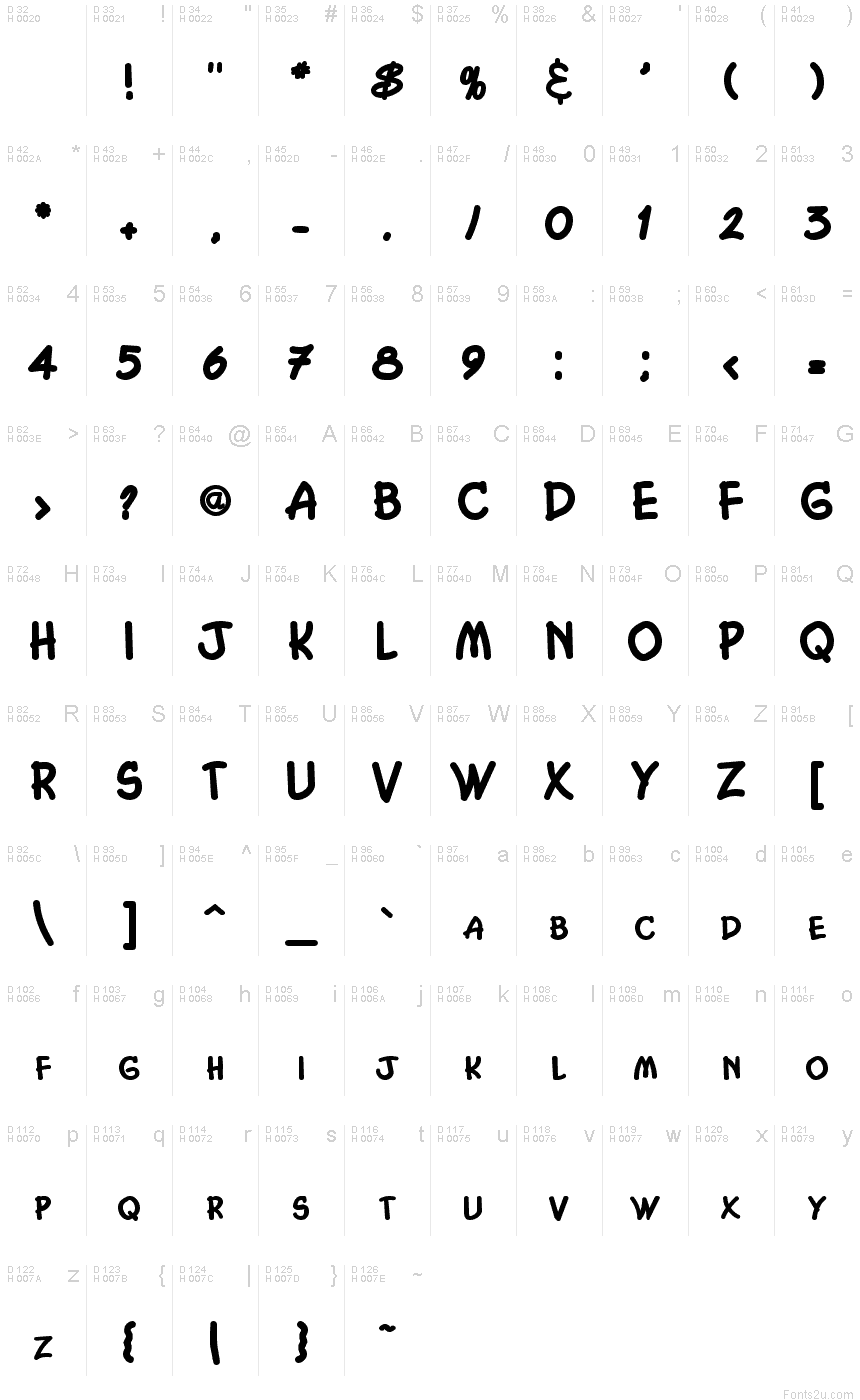
Chasm Bold di Bay Animation è un font calligrafico gratuito con tratti spessi e densi, che sembrano disegnati con un pennarello a punta grossa su un cartellone. Le lettere rimbalzano delicatamente sulla riga, con forme arrotondate e irregolarità giocose che conferiscono alla famiglia Chasm un calore amichevole e un aspetto da cartone animato. È abbastanza audace da catturare l'attenzione, ma con bordi morbidi, per cui non risulta mai invadente o rigido.
Utilizzando Chasm Bold, puoi portare un'energia rilassata e adatta ai bambini in materiali didattici, inviti per feste, packaging artigianali, fumetti, post sui social e loghi divertenti. Questo font gratuito si legge chiaramente anche in grandi dimensioni, dove le sue curve morbide e il ritmo vivace risaltano davvero. Per un abbinamento semplice, usa Chasm Bold per i titoli e accostalo a un font sans serif geometrico pulito per il testo di accompagnamento.
Mappa dei caratteri di Chasm Bold